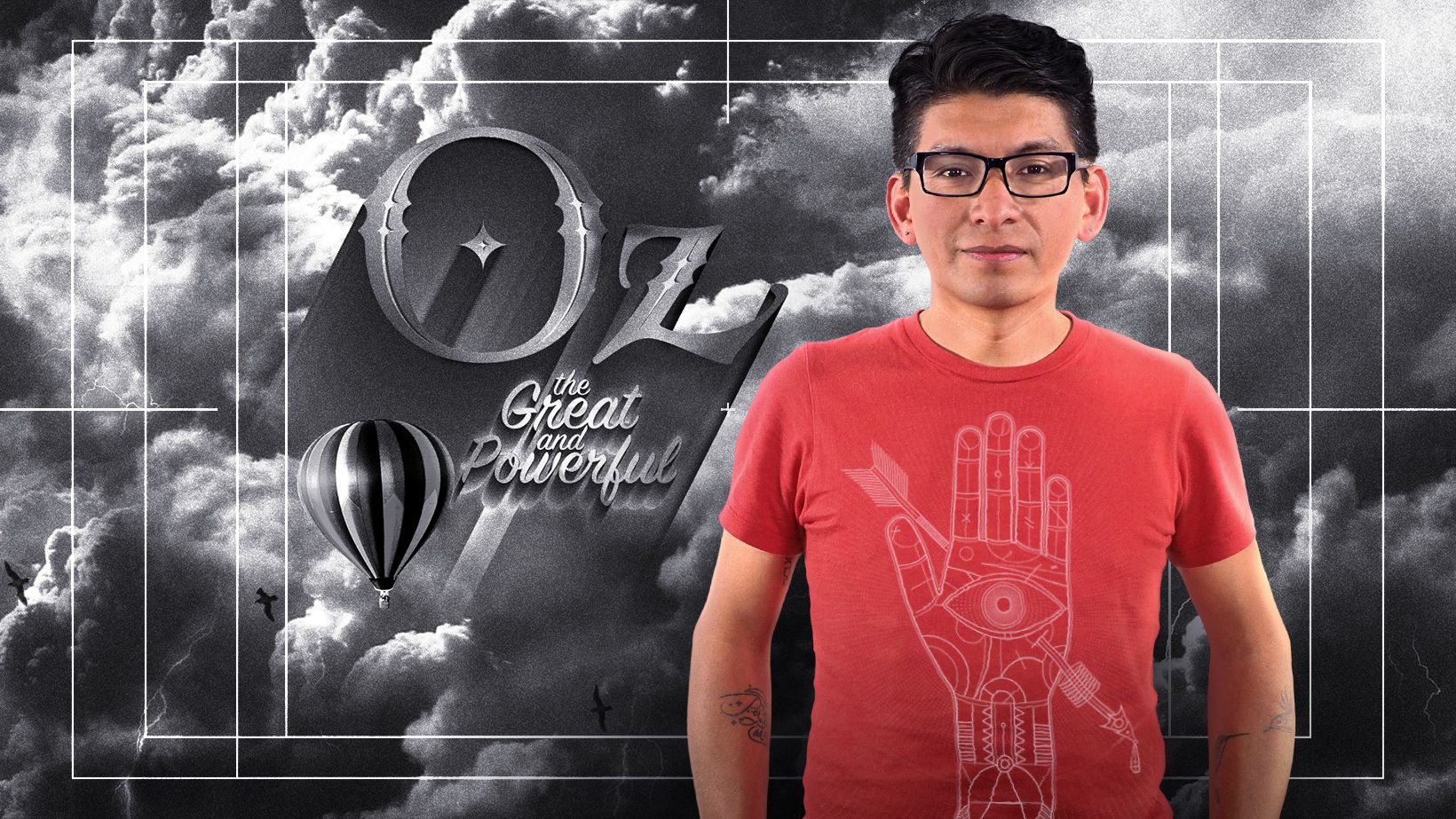
Für viele beginnt ein Film in der ersten Szene, für andere im Abspann, wo das Thema und der Ton des Stücks erblickt werden, um die Erwartungen in der Öffentlichkeit zu wecken, was José Luis Coyotl, Grafikdesigner und Regisseur, vorsieht Der Kunst widmet er sein Berufsleben mit Details, die so funktional und kraftvoll wie Typografie sind, und arbeitet unter anderem für Studios wie Warner Brothers, Walt Disney, ESPN und Universal.
In diesem Kurs lernen Sie den kreativen Prozess zum Erstellen von Credits für Film-, Fernseh- und Videoprojekte.
Zunächst kennen Sie die Arbeit von José Luis Coyotl, seine persönliche Geschichte, seine Leidenschaft für Design und Typografie und seine Haupteinflüsse.
Als Nächstes lernen Sie die wichtigsten technischen und narrativen Konzepte zum Erstellen von Kredit-Titeln kennen, z. B. Skript, Zeit, Struktur, Bewegungsdesign, Formate und Anzeigebereiche.
Sie werden die Bedeutung des Bildes bei der Gestaltung von Credits als Generator der grafischen Sprache in audiovisuellen Stücken, Typografie und deren Anwendung in Sequenzen für Kino und Fernsehen sehen.
Später werden Sie einen Film auswählen, um Ihre eigenen Credits zu bearbeiten. José Luis wird "Psycho" von Alfred Hitchcock auswählen, aber Sie können den auswählen, der Ihnen am besten gefällt. Sie analysieren das Thema, die erzählerischen Elemente und die technischen Aspekte.
José zeigt Ihnen seinen Prozess, um ein Konzept zu definieren und ein Moodboard zu erstellen. Anschließend entwickeln Sie Kompositionen in einer Reihe von Styleframes, mit denen Sie die endgültige Sequenz und die Elemente, aus denen sie besteht, visualisieren können: Farbe, Einstellung, Art der Aufnahmen und grafische Behandlung der Elemente.
Sobald das Konzept abgeschlossen ist, kennen Sie in der Produktionsphase den Prozess von José Luis, um es zu entwickeln, und später werden Sie sehen, wie Sie all dies zu einem endgültigen Bewegungstest bringen können.
Sie entwerfen die Abfolge der Credits für einen legendären Film. Der Lehrer wird Alfred Hitchcocks "Pshycho" machen, aber Sie können den gewünschten auswählen.
Dieser Kurs behandelt das Design von Titeln und Abspännen für Film, Magazine und Verlagsprojekte und verbindet Typografie, Motion Graphics sowie grafische Experimentiertechniken, um eindrucksvolle und ausdrucksstarke visuelle Sequenzen zu schaffen.
Ja, der Kurs begleitet dich Schritt für Schritt bei der Konzeption, Gestaltung und Animation von Abspann-Sequenzen, inklusive Bewegung, Sound und individuell gestalteter typografischer Elemente.
Im Verlauf des Kurses erstellst du praktische Projekte, die du in dein Portfolio aufnehmen kannst und die deine Fähigkeiten im Titel-Design, Motion Graphics und Art Direction für Film und Publikationen zeigen.